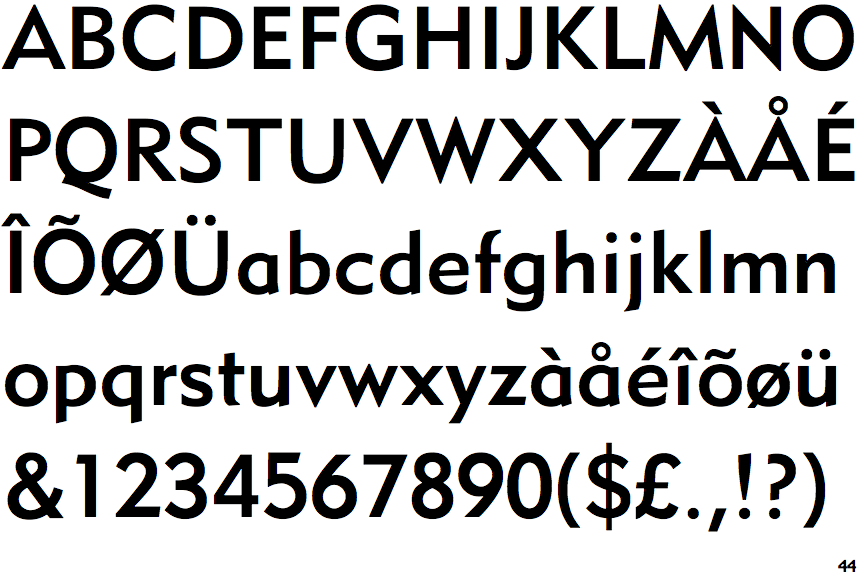
U-Bahnhof Berlin-Krumme Lanke
Kann mir jemand sagen, um welche Schrift es sich handelt? Sie wurde in Leuchtkästen an der Fassade des Berliner U-Bahnhofs Krumme Lanke angebracht. Das Haus ist aus den 20er Jahren, der Architekt Alfred Grenander. Neubau nach Originalplänen 1989.
Ist das nicht völlig unpassenderweise die NIVEA-Hausschrift?
Nein. Der Querbalken im A sitzt zu hoch, das G passt gar nicht. Identifont hat kein Sample auf der Seite für die DH Sans und die Links dort laufen ins Leere und heute scheint nicht mein Tag, Monat oder Jahr zu sein. Die DH-Sans ist wie auch die Opel Sans auf der Metro #2 aufgebaut.
Ist eben eine krumme, und dabei auch noch lanke Version eine Nivea-ähnlichen Schrift. Ich musste übrigens auch an Nivea denken - schon wegen des Farbschemas der U-Bahn-Schilder
Bei dem Farbschema denke ich aber auch an die Erbar Grotesk. Viele Schilder in Neufünfland waren vor unserer Besetzung in diesem Farbschema mit der schmalfetten Erbar. Auch bei uns gab es gelegentlich die schmale Erbar in diesem Farbschema, so auf Streichholzschachteln (Welthölzer). Das G passt zwar nicht zur Erbar Grotesk, aber ansonsten sehe ich da durchaus einen Ansatz. So hatte die Erbar Grotesk IMHO auch einen (wenn auch gerne verheimlichten) Einfluss auf die Metro #2. Ich würde da als Inspiration für diese Schrift auch von einer spitzen Erbar Grotesk ausgehen. In den Lettern sehe ich irgendwie noch die Vorfahren der alten geometrisch konstruierten Grotesk aus dem Deutschland der 1920er.
Danke! Erbar war mein erster Gedanke, nur das G paßt eben nicht. Deshalb hatte ich gefragt. Es gab 1989 noch jede Menge Schilderwerkstätten mit einem höheren Teil Handarbeit, da wird das dann wohl so gemacht worden sein.
Oder man hat sich an Alfred Grenanders Originalentwürfe für diesen Bahnhof aus den späten 20ern gehalten, und hier diese ja deutlich aus der „klassischen Moderne“ stammenden Schrift so genau wie möglich nachempfunden.
Im Westen war das seltener, aber hier hatten „alle“ ja Zugriff auf wesentlich mehr Resourcen. Aber auch hier gab es bis in die 1980er durchaus eigene Interpretationen von „echten“ Schriften durch die Schildermaler. So gesehen ist das alles wenig verwunderlich. Aber das G wirft einen zuerst mal aus der Bahn. Alle mir bekannten „spitzen“ Grotesk aus der Zeit vor/um 1930 haben keinen senkrechten Balken. Oder kennt da jemand eine Ausnahme?
Nur zur Vergewisserung: Der U-Bahnhof Krumme Lanke war ein Westberliner. Und eine Werkstatt als Ausbildungsbetrieb für Schildermaler habe ich Ende der 90er Jahre noch kennengelernt, ebenfalls im Westteil der Stadt.